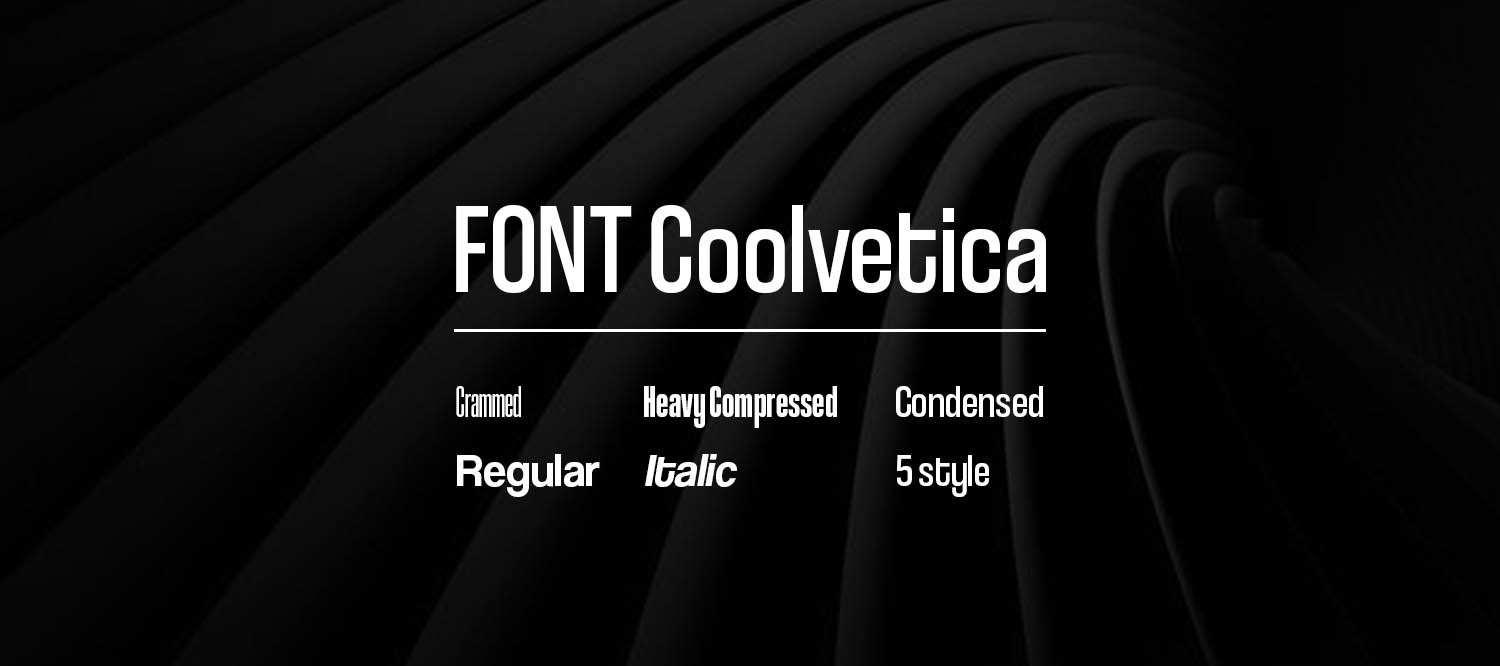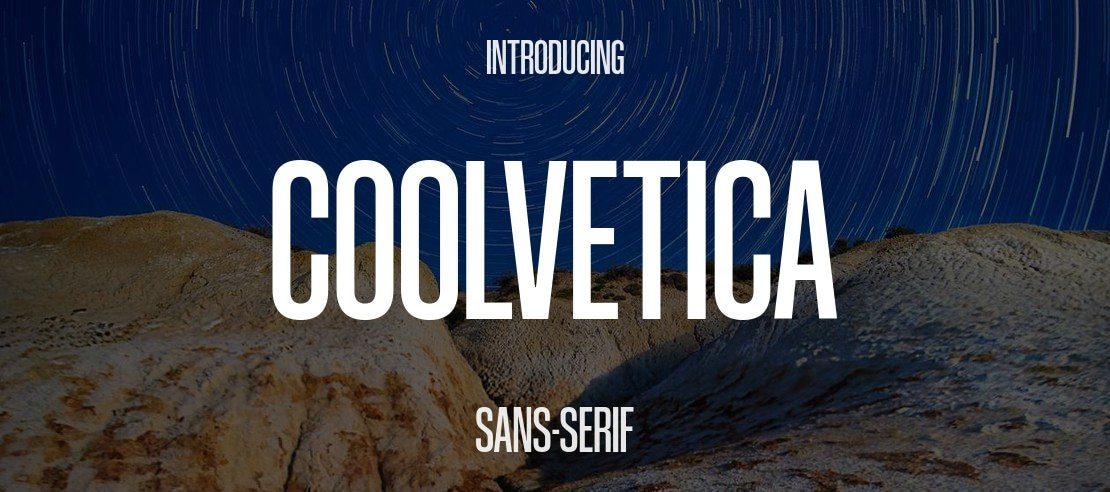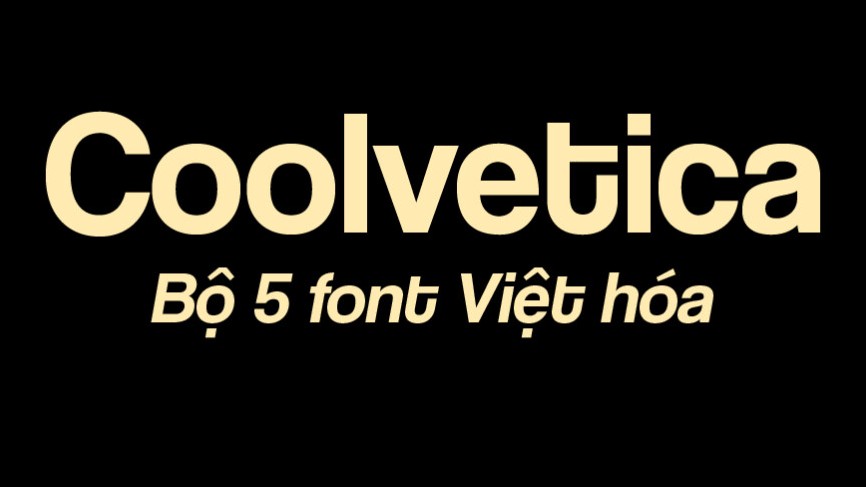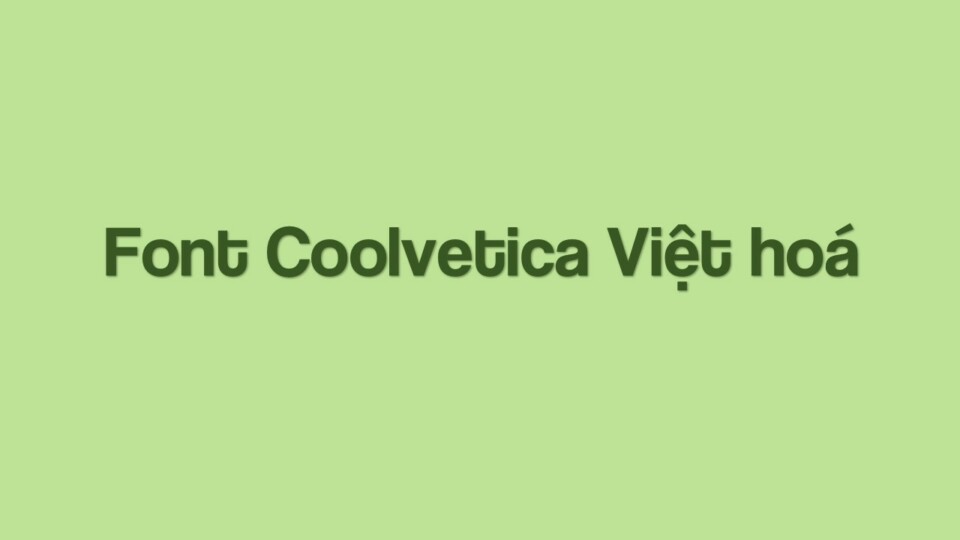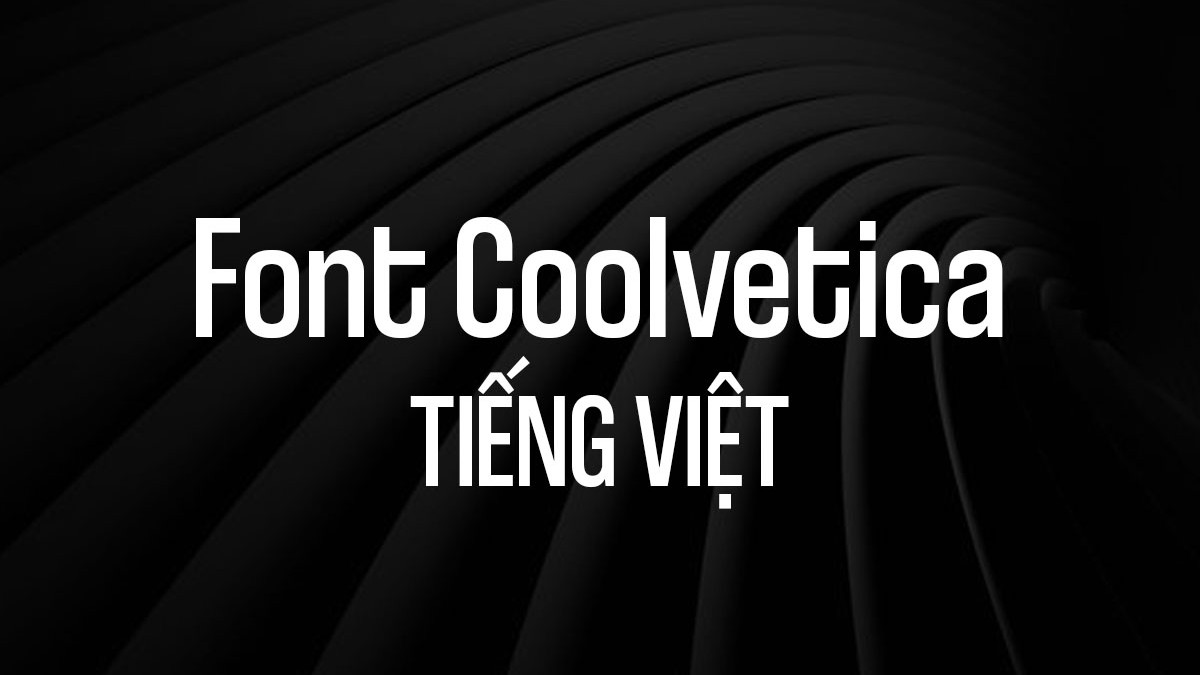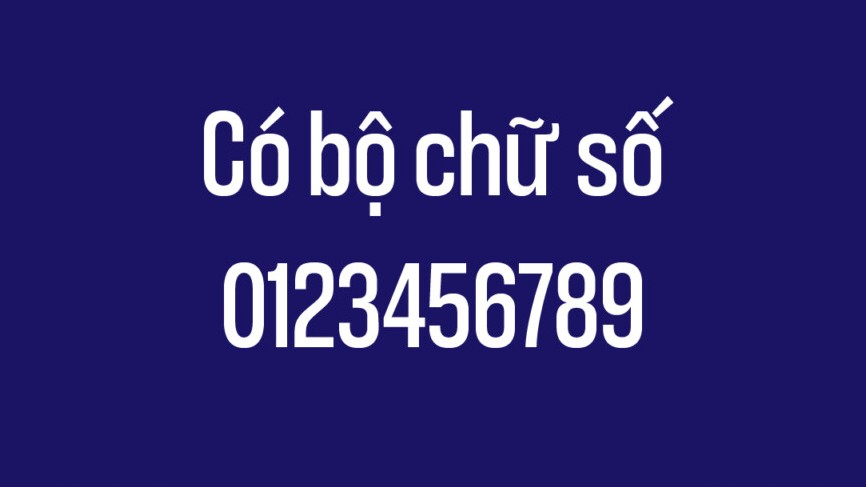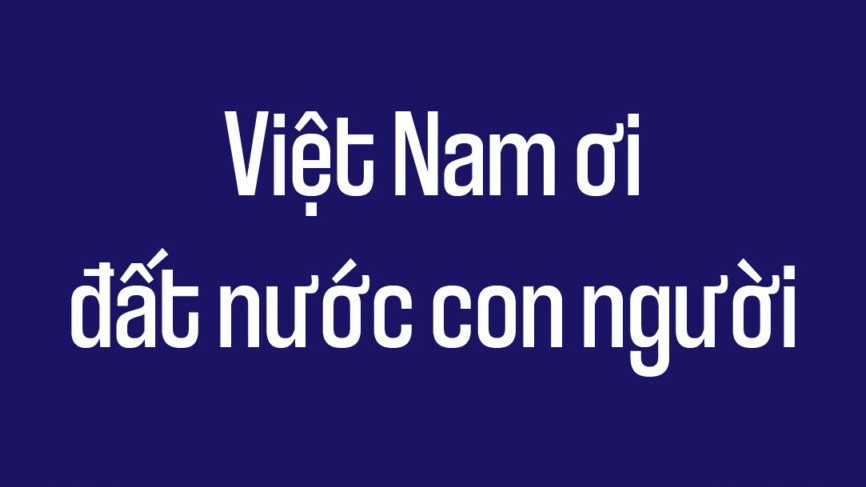
Font Coolvetica là gì và phong cách thiết kế đặc trưng?
Font Coolvetica là một bộ phông chữ thuộc dòng Sans-serif hiện đại, được sáng tạo bởi nhà thiết kế Ray Larabie vào những năm 1990. Lấy cảm hứng từ phông chữ Helvetica kinh điển nhưng được biến tấu với các đường nét phóng khoáng và khoảng cách ký tự khít hơn, Coolvetica mang lại cảm giác thân thiện, trẻ trung nhưng vẫn vô cùng vững chãi. Đây là lựa chọn cho các logo thương hiệu thời trang hoặc các ấn phẩm truyền thông dành cho giới trẻ.
05 Ứng dụng phổ biến của font chữ Coolvetica trong thực tế
Vẻ đẹp hiện đại và tính đa dụng của font Coolvetica Việt hóa giúp nâng tầm giá trị cho nhiều ấn phẩm truyền thông của đơn vị:
- Xây dựng nhận diện thương hiệu Startup: Coolvetica cực kỳ phù hợp để làm logo nhờ nét chữ sạch sẽ, cứng cáp. Sự minh bạch trong cấu trúc chữ giúp khách hàng cảm nhận được sự năng động và tin cậy của doanh nghiệp ngay từ cái nhìn đầu tiên.
- Sản xuất bao bì thực phẩm và đồ uống: Sử dụng font Coolvetica regular Việt hóa cho các phần tên sản phẩm trên vỏ hộp giấy hay nhãn dán chai trà sữa. Độ rõ nét của phông chữ này tạo thiện cảm về sự hiện đại và chất lượng sản phẩm.
- Gia công in ấn trên các sản phẩm văn phòng: Logo dùng Coolvetica in trên bình giữ nhiệt kim loại hoặc sổ tay da tạo vẻ ngoài thời thượng. Công nghệ in tại In Viva giúp các đường nét hình học hiển thị sắc sảo, không phai màu theo thời gian.
- Sản xuất thẻ đặc quyền và Voucher tri ân: Phông chữ này là lựa chọn lý tưởng cho các dòng chữ vinh danh trên thiệp mời sự kiện. Sự kết hợp giữa nét chữ vững chãi và kỹ thuật in ép kim nhũ vàng giúp tấm thẻ trở nên vô cùng sang trọng.
- Thiết kế Catalogue và hồ sơ năng lực: Khả năng phân cấp thông tin mạnh mẽ của bộ phông này giúp các bảng biểu, số liệu trong báo cáo hiển thị khoa học, hỗ trợ đối tác dễ dàng theo dõi thông tin doanh nghiệp.
04 lưu ý kỹ thuật khi sử dụng font chữ Coolvetica Việt hóa
Để hệ thống ký tự không chân hiển thị sống động và bền màu trên các thành phẩm thực tế như túi giấy hay quà lưu niệm đối tác, designer cần chú trọng:
- Kiểm soát khoảng cách ký tự: Do Coolvetica regular có đặc trưng là các chữ cái nằm rất sát nhau, khi in lụa trên túi vải hoặc các bề mặt nhám, bạn nên tăng nhẹ khoảng hở để mực không bị bết dính gây mất nét.
- Tối ưu đường Path cho gia công bế nổi: Đây là bước quan trọng khi sản xuất hộp cứng cao cấp dập nổi logo. Kỹ thuật viên cần làm mượt các điểm neo trong file vector của phông chữ Coolvetica giúp khuôn kẽm thực hiện chính xác, tạo hiệu ứng nổi khối rạng rỡ mà không làm rách giấy mỹ thuật.
- Thiết lập hệ màu CMYK chuẩn: Phông chữ này thường đi cùng các màu đơn sắc tối giản. Designer cần hiệu chỉnh hệ màu CMYK và yêu cầu xưởng in mẫu thử để đảm bảo màu chữ sau in không bị ngả xám so với bản vẽ máy tính.
- Lựa chọn định lượng giấy phù hợp: Khi sử dụng Coolvetica cho các tiêu đề lớn, in trên giấy Ivory hoặc giấy có độ trắng cao sẽ giúp màu sắc của chữ hiển thị trung thực và bắt mắt.